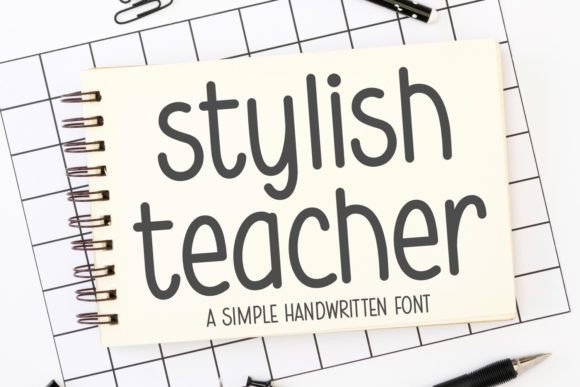
Stylish Teacher
Stylish Teacher – La police manuscrite qui dynamise vos créations
Vous cherchez une typographie à la fois adorable et polyvalente pour vos projets créatifs ? Ne cherchez plus : Stylish Teacher est la solution idéale. Cette police manuscrite, inspirée du style d’un professeur branché, insuffle couleur et énergie à chaque texte, que ce soit pour du print ou du digital.
Pourquoi choisir Stylish Teacher ?
- Design vibrant – Des courbes ludiques et des traits arrondis qui attirent immédiatement l’œil.
- Extrême polyvalence – Parfaite pour les affiches scolaires, les décalcomanies, les signalétiques enfantines, les notes personnalisées et le contenu web.
- Facile à lire – Malgré son aspect manuscrit, la police reste claire et lisible, même à petite taille.
Utilisations créatives de Stylish Teacher
Grâce à son style ludique, Stylish Teacher devient le compagnon parfait pour:
- Les projets scolaires : titres de présentations, couvertures de rapports, fiches de travail.
- Les décalcomanies et stickers : personnalisez cahiers, bouteilles d’eau ou notebooks.
- Les signalétiques pour enfants : panneaux d’accueil, panneaux de salle de classe, menus de cantine.
- Les notes personnalisées : cartes de vœux, invitations d’anniversaire, messages de remerciement.
- Le contenu digital : posts Instagram, bannières web, newsletters créatives.
Conclusion – Le choix incontournable pour vos projets créatifs
En résumé, Stylish Teacher est bien plus qu’une simple police manuscrite : c’est un véritable catalyseur d’inspiration. Sa capacité à mêler charme enfantin et professionnalisme en fait le choix parfait pour tous ceux qui veulent rendre leurs designs vivants, mémorables et SEO-friendly. Téléchargez dès maintenant Stylish Teacher et libérez votre créativité sans limites !